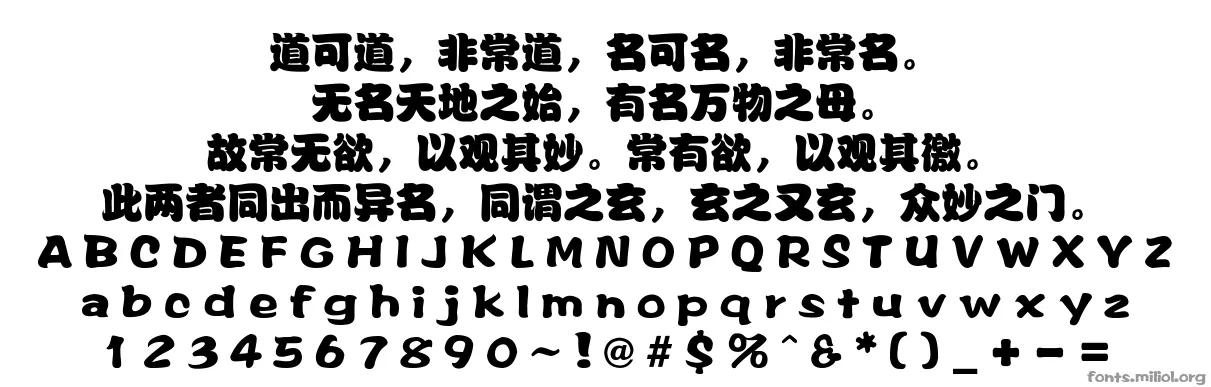
## 方正胖娃_GBK:一款充满童趣的中文字体
方正胖娃_GBK (FZPangWa-M18) 是一款由方正字库设计的中文字体,以其圆润可爱的字形和充满童趣的风格而闻名。这款字体专为儿童读物、卡通动漫、广告宣传等场景设计,能够有效吸引眼球,营造轻松活泼的氛围。
方正胖娃_GBK 字体的最大特点在于其“胖”和“娃”两个字。每个字都经过精心设计,笔画圆润饱满,字形憨态可掬,仿佛一个个活泼可爱的胖娃娃,充满童真童趣。同时,字体结构严谨,笔画清晰,易于识别,即使放大使用也不会显得臃肿。
除了字形设计,方正胖娃_GBK 还支持 GBK 编码,能够满足绝大多数中文场景的使用需求。无论是标题、正文还是装饰性文字,这款字体都能轻松驾驭,为您的设计增添一抹亮色。
总而言之,方正胖娃_GBK 是一款兼具美观与实用的中文字体,是您打造充满童趣和活力的设计作品的理想选择。